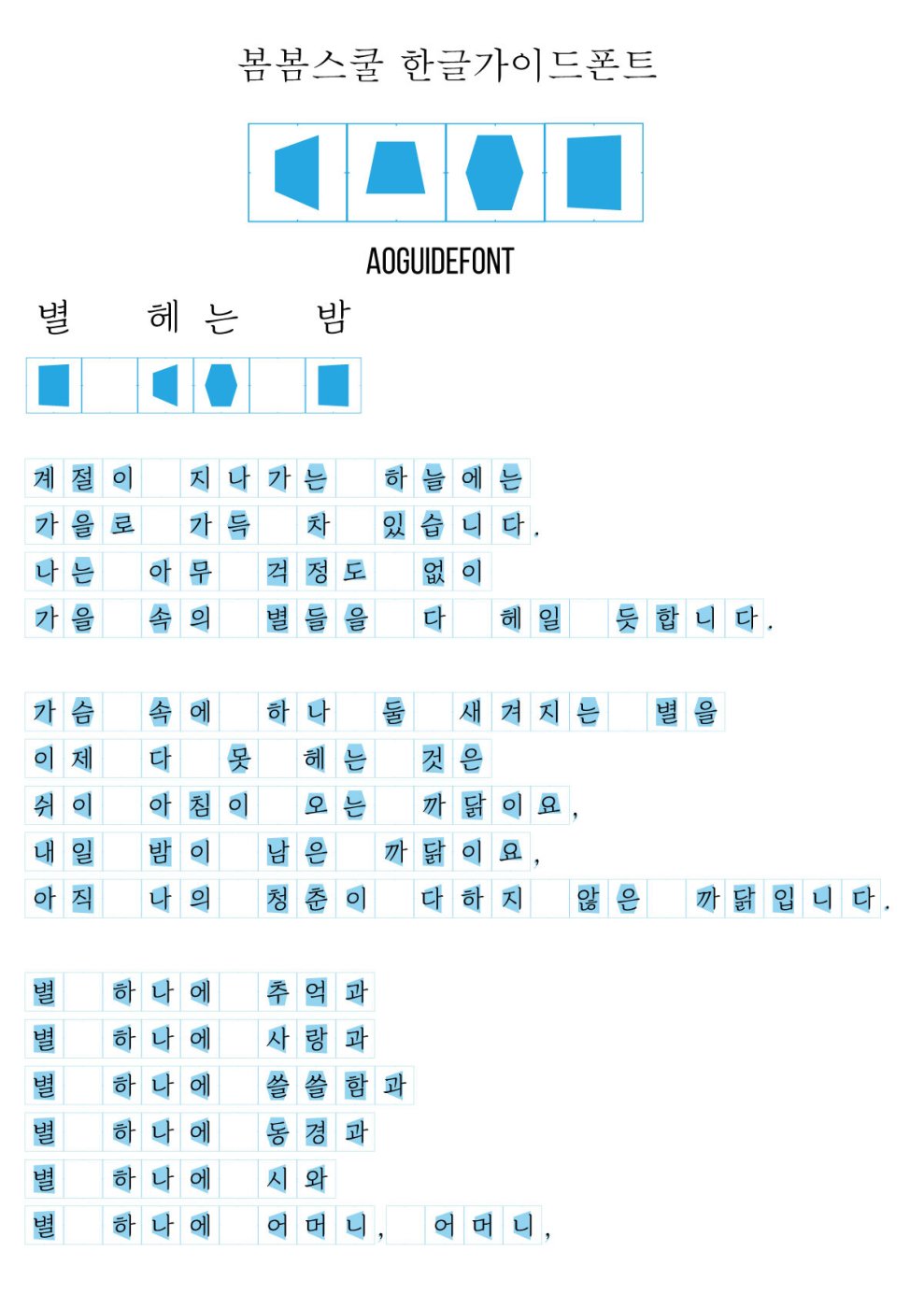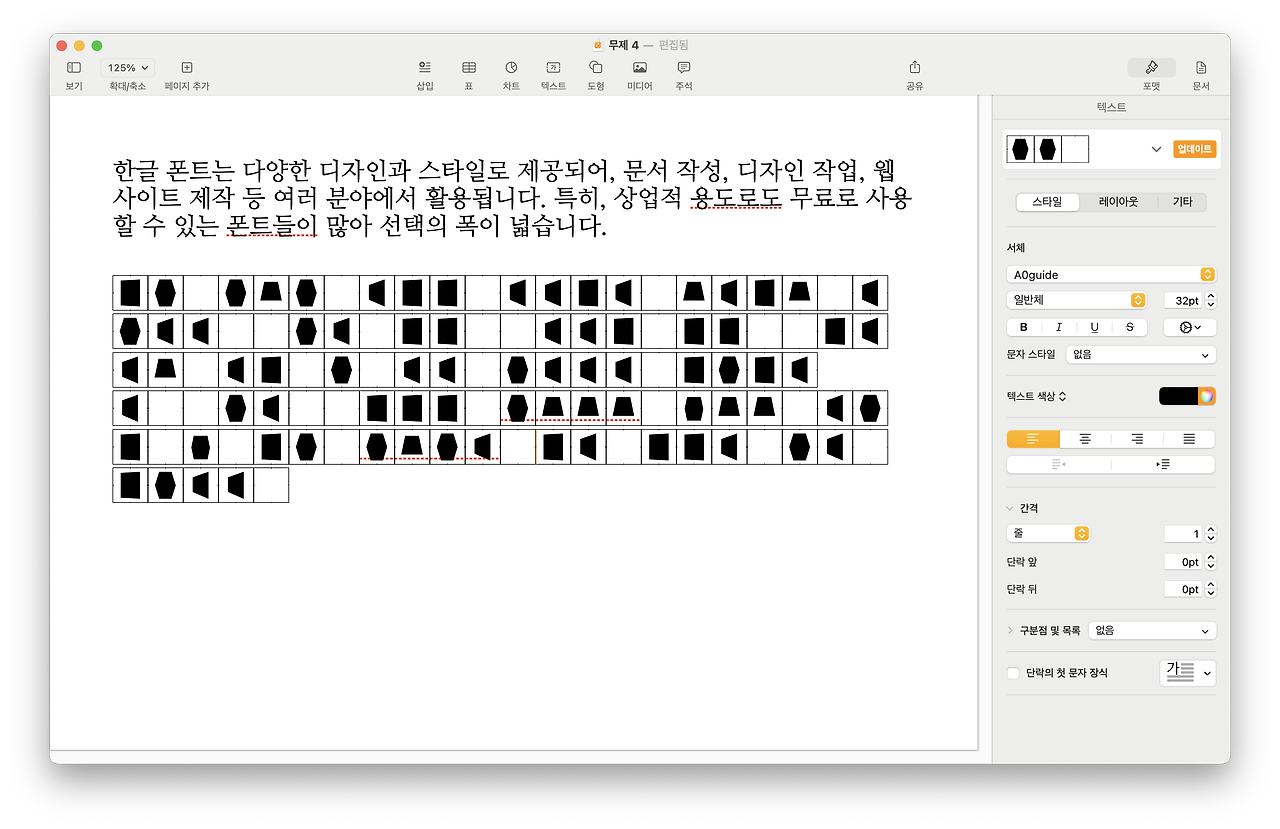
한글 가이드 폰트 - 손글씨 가이드
한글을 도형으로 표현한 독특한 가이드 폰트를 제작하였고 이제 마무리 할정도는 됐습니다.
손글씨 작업 -> 20자 작성 -> 가이드 폰트 제작-> 300자 내외 글씨쓰기 (한글, 영문, 숫자, 약물)
폰트 제작 으로 이어집니다.
한글을 쓰면 폰트를 가이드로 바꿀 수 있으며 필사를 할 때 바른 손글씨를 쓸 때 가이드로 활용이 가능합니다.
명언, 책속 문구, 등을 원고지 스타일로 변환하며 색상을 흐리게 인쇄하고 글을 쓰시면 됩니다.
파란색 30정도로 놓고 인쇄한 이후 글을 쓰면 정체스타일로 글을 쓸 수 있게 가이드를 제공합니다. 워드, 한글, 거의 대부분의 편집기에서 사용가능하며 개인사용은 무료이며 인쇄물, 도서, 상업적 용도로는 제공하지 않으며 자막이나 디컴파일 용도로 상업적 사용은 불가능합니다.